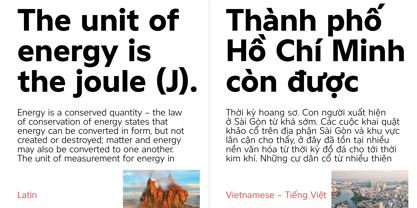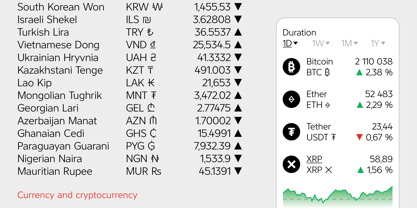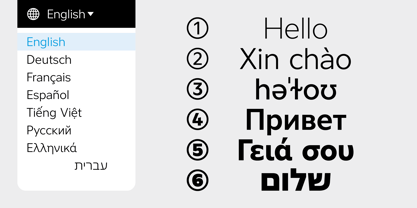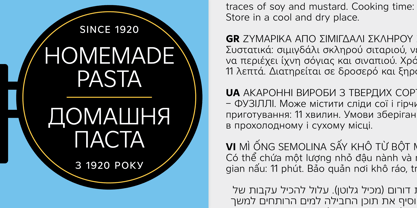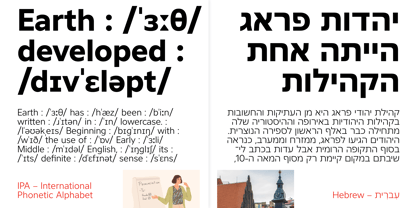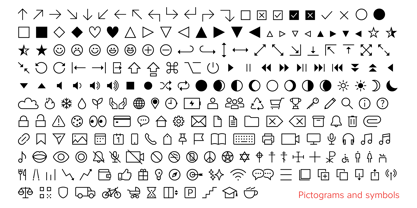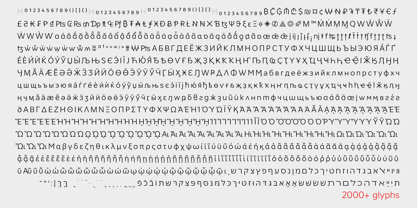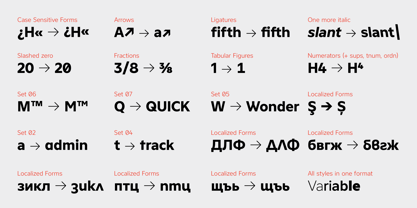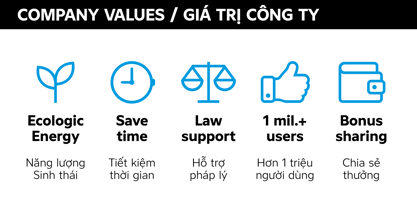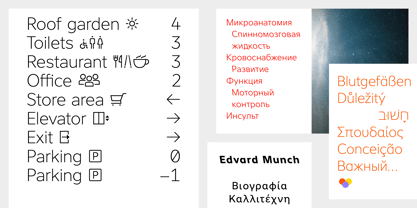
Atwic Pro
La familia tipográfica Atwic Pro fue diseñada por Martin Činčár y publicada por Caron twice. Atwic Pro contiene 19 estilos y opciones de paquete familiar. Más información sobre esta familia
Atwic Pro is a clean, simple sans serif typeface whose character aligns with Frutiger, Gill Sans, and Segoe. Today, the sans serif is a modern staple and arguably the defining visual language of contemporary text communication. Containing more than 2,000 characters, Atwic Pro supports four writing systems: Latin, Cyrillic, Greek, and Hebrew. It also covers Vietnamese, Pan-African Latin, the International Phonetic Alphabet (IPA), Bulgarian Cyrillic, polytonic Greek, national currency and cryptocurrency symbols, and pictograms (icons). Its extensive character set makes Atwic Pro a powerful communication tool and instrumental in global brand and campaign communications. Multilingual ingredient labels. Multilingual websites, apps, and conferences. Atwic Pro is well suited for neutral, universal use across both print and digital media. It performs reliably in posters, headlines, brand identities, websites, mobile apps, and wayfinding systems. For continuous text, we recommend the Regular and Bold styles; the high x-height and open endstrokes ensure good readability at smaller point sizes and when viewed from a distance. For larger point sizes, such as in posters and headlines, we recommend the Light and Black styles. Atwic Pro includes a range of style alternatives. Italics and Reverse Italics. A full phonetic alphabet, used in dictionaries to transcribe pronunciation. These features are complemented by a set of pictograms that support information navigation and can be used in website interfaces, chats, music and video players, wayfinding systems in buildings, and even as expressions of a brand’s values.